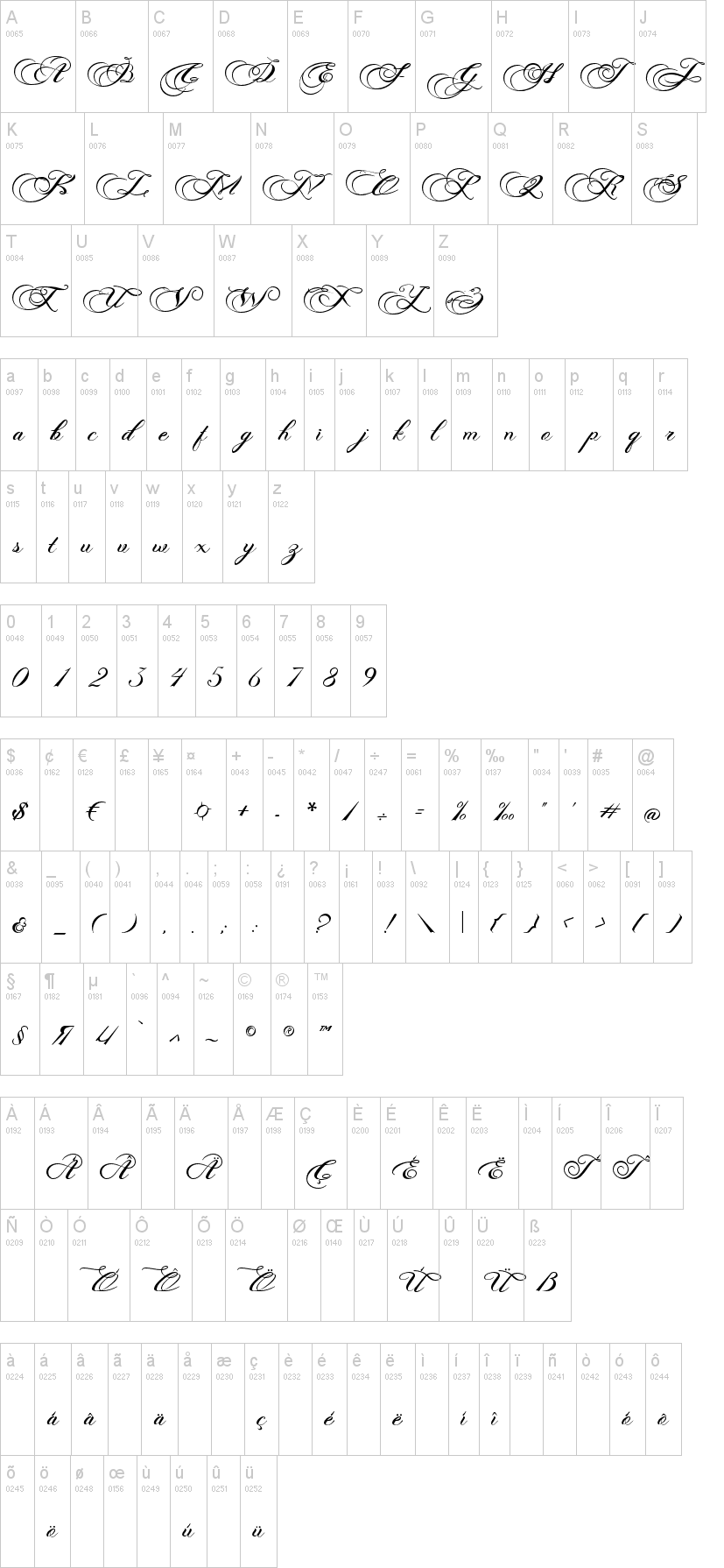
Photograph Script 是一款手写风格的脚本字体,它拥有温柔而柔软的笔触,可以创造出有趣而优雅的文字效果。它具有细腻的笔画,给人一种自然舒适的感觉,为设计师提供了一种更加自然的文字表达方式。它也可以用于节日卡片、海报、婚礼邀请函等,为设计师提供了更多的创意空间。内容介绍
Photograph Script是一款非常不错的手写艺术字体,具有很好的视觉感,适合于文化类的宣传设计、商业类品牌的广告和产品包装设计以及个性化文字排版等较多场景。